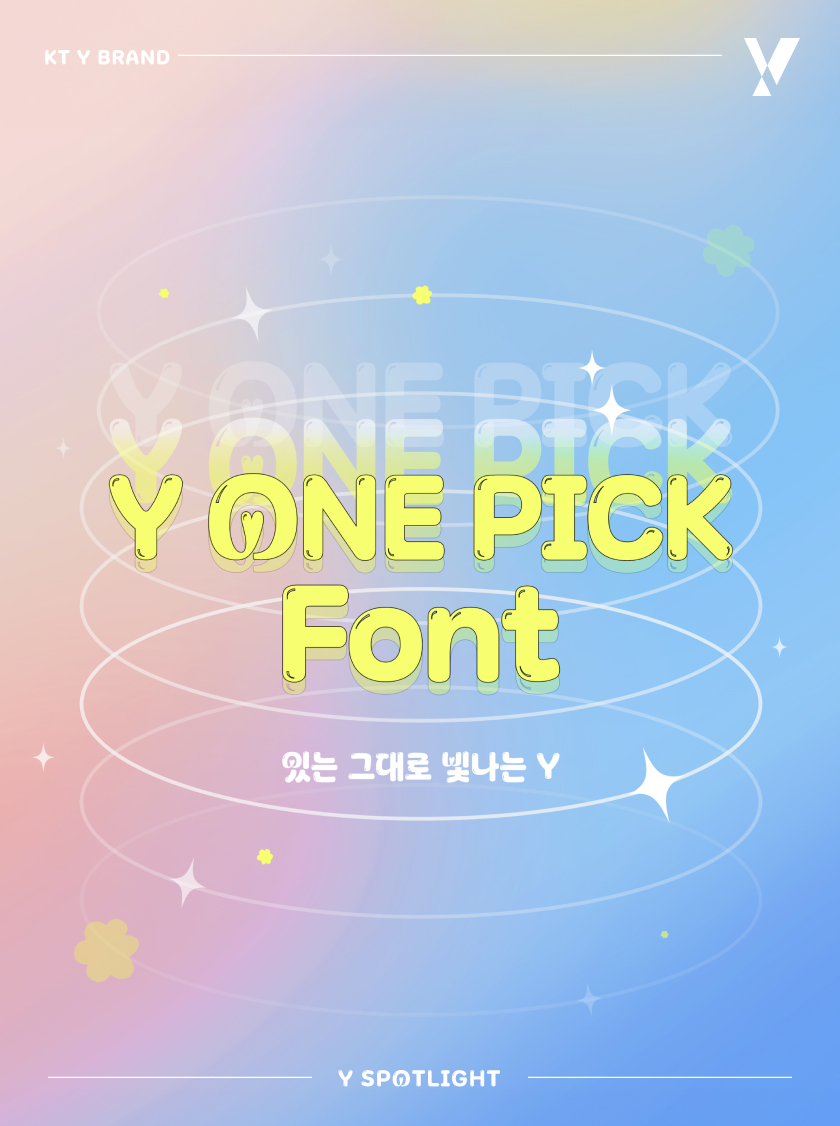
Y세대만을 위한
스포트라이트의 형상을
시각화하여 설계된
Y 브랜드만의 서체입니다.
Y BRAND FONT
나를 위한 이모지 33종
'와''이'와 연계된 한글 낱자 중 자주 표현하지 않는 낱자에 이모지 33종 매치
Y의 개성을 담아
스트릿한 감성의 아이콘이
숨겨져 있는 Y의
와이드 서체입니다.
Y BRAND FONT
Y개성을 담아 와이드하고
스트릿한 감성의 이모지 37종
온유한 곡선이 강조된
부드럽고 따뜻한 감성의 서체로
유니버스를 표현한 아이콘들이
숨겨져 있어요~!
Y BRAND FONT
자신만의 색으로 빛나는 Y의 유니버스를
기하학적 그래픽으로 표현한 아이콘 40종
디지털 환경에서
나고 자란
Y의 디지털 네이티브
아이덴티티를 담은
비트맵 서체입니다.
Y BRAND FONT
옛날 콤퓨타의 추억을
불러일으키는
레트로 비트맵 스타일
아이콘 44종
Y이드스트릿체
Y유니버스체
Y콤퓨타체
Y의 밝고 활동적인 모습을
네잎클로버에 담은
발랄하고 통통 튀는 서체입니다.
Y BRAND FONT
Y의 행운을 응원하는 마음을 담은
네잎클로버 스타일 아이콘 36종
Y페어링체
Y최애체
Y클로버체
Y 너만을 비춤체
Y이드스트릿체
Y유니버스체
Y콤퓨타체
나만의 최애를 향한
Y의 반짝이는 애정을
자유로운 곡선과
하트 형태로
표현한
Y서체입니다.
Y최애체를 모바일에서도 사용해보세요!
Y최애체 Regular체는
모바일 환경에서도 사용이 가능합니다.
Y BRAND FONT
Y를 향한 애정하는 마음을 듬뿍 담은
하트 스타일 PC 아이콘 41종
* PC에서는 볼드체로 아이콘 입력이 가능합니다
모바일 환경에서도 사용 가능한
애정 듬뿍 하트 모양 아이콘 6종
Y페어링체
Y최애체
Y클로버체
Y 너만을 비춤체
Y이드스트릿체
Y유니버스체
Y콤퓨타체
끊임없이 연결되는
Y의 라이프스타일을
자유로운 선으로 표현한
Y페어링체 입니다.
Y페어링체를 모바일에서도 사용해보세요!
(PC/모바일 모두 사용 가능)
Y BRAND FONT
나란히 붙어 있을 때 꼶앪읾
부드럽게 연결되는 페어링 아이콘 44종
*볼드체와 레귤러체 모두 딩벳 아이콘 입력이 가능합니다.
*Y페어링체 설정 후 위 문자를 입력하면
딩벳 아이콘이 표현됩니다.